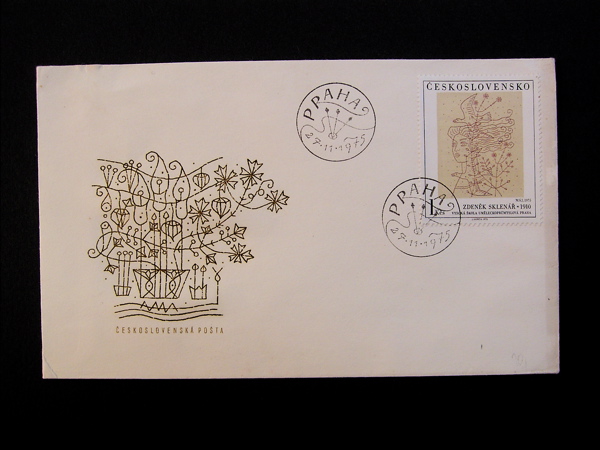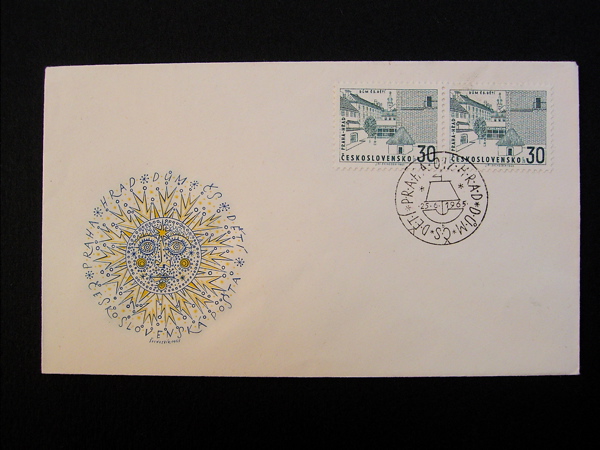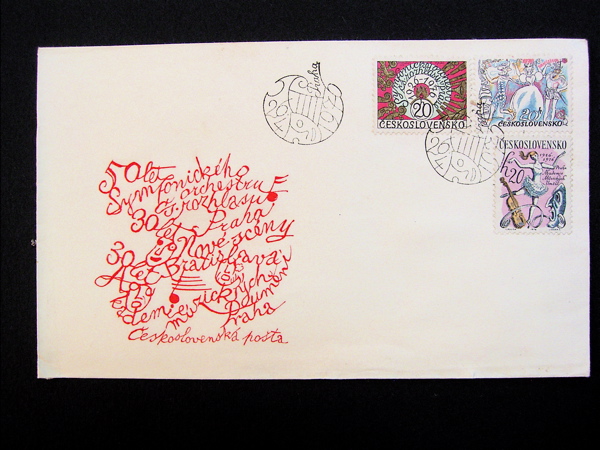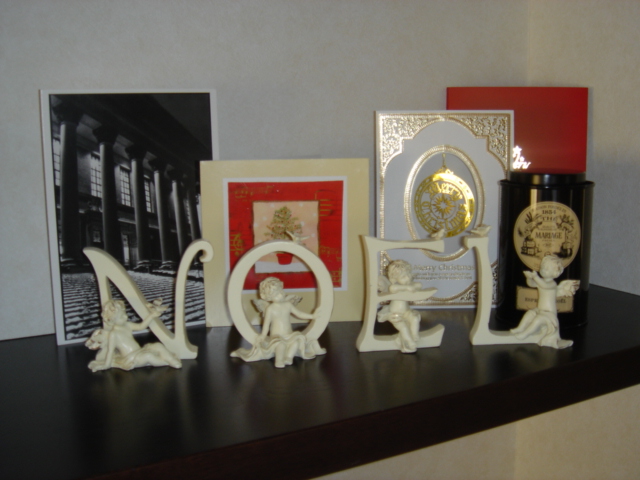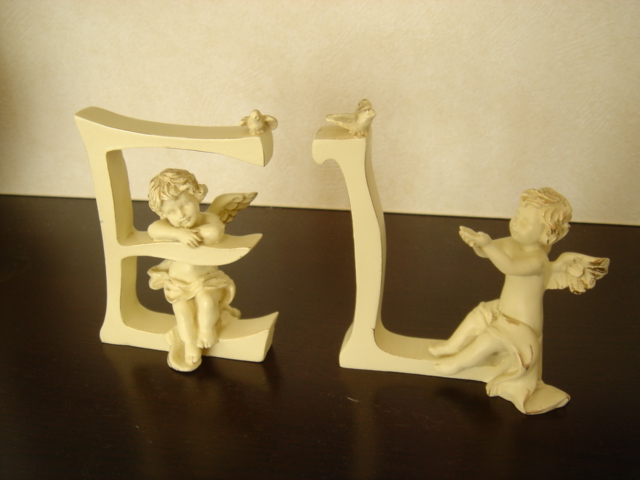
クレーのビュルギ・スケッチブック
大掃除をしていてもなかなか片付かないのは、整理する時にいちいちじっくり見入ってしまったりするからなんですよね。
きのうはパウルクレー協会会員限定版のビュルギ・スケッチブックのファクシミリでしばらく時間をとってしまいました。
寸法や体裁ともにオリジナルにかなりの程度忠実に模しているそうです。製本まで全部手作業の布張りのスケッチブックです。小さなサイズですが、中身は濃い!持っているだけで満足のスケッチブックなのです。
しかし、それも面白いのですが、一緒について来た解説本がもっとおもしろい!。私は初めて見ましたが、製本前の状態で送られてきているのです。
寒冷紗まではついていますが、表紙はなく、中身のページも袋状ですし、天地も小口も切る事を前提としてトンボが付いています。
これをどんな風に製本するかは、所有者のお好きな様に、と言う訳なのでしょう。
私の近くには、とてもユニークな製本をしてくれるモジトルのメンバーがいますので、イメージが固まったらお願いするつもり。それを考えるだけでも楽しみです。
手帳は何をお使いですか
早いもので明日は大晦日です。手帳もカレンダーも2005年版さようなら、ですね。コーヒーこぼしちゃってやけにふくらんでしまった
今年の手帳よ、ご苦労さん。
先日来年用の手帳を買おうとお店に行きましたが、ゆっくり選ぶ時間がなくて例年と同じものを購入してしまいました。
このところ使っているのはQuo Vadisのもので1週間見開き、時間が縦に刻んであるタイプです。
予定を書き込むには便利、でも無地のページがもっとあるといいな、とか日曜の欄が小さいので使いにくいな、などなどちょっとした不満はあるものの・・・文庫本サイズなのは気に入っています。
カバーは革製、ビニール、いろいろ選べます。ソニープラザには環境に配慮したカバーというのもありました。革のいいのを買おうか、他の手帳に乗り換えようか、それはまた来年考えることにして。
写真は、ちょっと飽きてしまったし寒いので冬バージョンに変身したカバーです。毛糸モコモコをくっつけて気分だけも暖かく。
アンネの日記
大掃除をしていたら古びた新聞が出てきました。以前気になって取っておいた1998年5月朝日新聞日曜版です。
「100人の20世紀」というシリーズで、この回はアンネ・フランクでした。
まず目に留まったのは、この壁に書かれた文字です。アンネが通っていたアムステルダムのモンテッソーリ・スクールが戦後アンネを記念して、アンネ・フラン ク・スクールと名付けられました。道路に面した壁には日記の一節が書かれています。壁と文字の色は紫とオレンジで、はっと目を引きます。 手書きの文字なので、訴えかける力が絶大です。
この壁に書かれた一説が日記のどの部分かはわかりませんが、私は何度か彼女の書いた文章をカリグラフィーの作品で使っています。特に有名なのはこの文章です。
In spite of everything, I still believe that people are truly good at heart.
「すべての状況にも関わらず、人々が心の中では本当は善良なのだと私は信じています」
(一節の全文は追記の方に書きましたので、そちらをご覧下さい)
たとえ大きな絶望の中でもけなげに希望を持っていた十代の少女の書いたこの文字を見ると、世の中に戦争がなくなり平和な世界が来るようにと、祈らずにはいられません。
来年が争いのない平和な一年になるといいですね。
この大掃除に出て来た黄ばんだ新聞。捨てずに取っておこうと思います。
粘土のアルファベット
以前、ブログで粘土のアルファベットを紹介しましたが、自分でも作ってみたくて、制作者の小松さんに粘土のアルファベットの1day ワークショップをしていただきました。
平らな粘土の上にアルファベットの切抜きをおいて、カッターを使って、形を切り出していくのですが、刃を垂直に入れて切り出すのがなかなか難しく、集中力のいる作業でした。切り出した後は、表面をならす作業がやりやすいのですが、なかなかフゥ...... ならしながら、先生のかわいいでしょ!という言葉が印象的。確かになでなですると可愛い気になってきます!要領を得た方々は、どんどん進んでできていましたが、私はといえば、1回で1個がようやくなもので、3回にわたってやって、ようやく3種を作りました。
写真奥のMO、モノグラムに挑んだ1作目、これは大変でした。途中で割れてきてしまいましたが、お助け、先生の技に感心!2作目ABC、2回にわたって作り、なんとかABCになりました。乾いて立たせたら、Bがひっくり返ったけれど,,,,,、3作目、noel、全WS終了後、夜ひとりやって仕上げました。ABCもnoelも形がコロンとしていてかわいいです!白い粘土のほうがよかったかなあ。
初めての粘土、とっても新鮮で楽しかったです!カリグラフィーでもいろいろな工夫された道具の数々見てきましたが、粘土用の先生の手作り道具にはホ〜!でした。手作りの醍醐味を感じました。
書くだけではなく、何か手で作るという楽しさは、心を豊かにしてくれます。1年の締めくくり、あったかな気持ちになったワークショップ。小松さんありがとうございます!!!
懺悔のシーズン
国内では三連休のクリスマス行事も終わり・・・お正月に向けて街が変化しつつあります。
日本独特の風景ですね。
キリスト様の国では1月の三聖節(6日かな?)まではクリスマスっぽい雰囲気が続くようですから・・・。
さてさて・・・今年も「やってしまった・・・懺悔のシーズン」です。色味のない部屋を楽しくしてくれたgreeting cardたち。みんなからの優しい心遣いが伝わってきて、冬の季節なんか吹き飛ばしてしまいそうな暖かさで身体も心も包まれます・・・。
それなのに・・・、私といえば、サンタとの交流は断ち切り、25日に海外向けのカードを必死に書き上げていたのでした。もう聖なる日になんか間に合いません!日本人的に「new year!」を勝手に押し付けているのです〜。
時々は間に合ったりもしますが、大抵はズレにズレコミます。そんな私のカードでも海の向こうのみんなは喜んでくれるわけです!「あ〜、神様よりきっと優しい!」
e-mailの手軽さもありますが、やはり手書きが・・・形あるものが・・・絆を深めます。毎年そんな風に感じます。
ちなみに・・・サンタはカトリックの国では活躍しないそうですね・・・。ドイツ語の先生が説明してくれました。オーストリアから来ていた先生でしたが、「サンタなんかいないよ!クリストキントだよ!」って言ってました。クリストキント=幼キリストですね。
まぁ、世界の半分以上はクリスマスは祝わないわけですから・・・などと言い訳、言い訳!心から懺悔して・・・来年こそは・・・鬼も笑っちゃうような決意です!
チェコの封筒デザイン
クラスの生徒さんのE子さんが,教室に持って来て見せて下さったチェコの封筒デザインです。ほとんどが1960年代のアンティークもので、切手と消印と封筒に印刷されている絵が一体になった実にと〜っても不思議な一品なのです。
クリックして拡大版をじっくり見てください。切手のデザインが消印にも生かされていて、さらに封筒に印刷されている絵にも同じデザインが繰り返されていま す。先に切手と消印があって、それに合わせて印刷したのでしょうか。面白い線で書かれている文字が何とも言えず、いい味を出していますよね。
このアンティークの封筒は大阪の有名な雑貨屋さんでみつけたそうです。こんなお宝、私もみつけてみた〜い!!
天使といっしょに
文字好きを公言しているので、それに関わるものをいただくことは多いのですが
今年のクリスマスには文字そのものというプレゼントをいただきました。
このNOEL、一人ずつ天使が共にいるのです。
腕にあごをのせている天使もかわいいですね。何か考えごと?Lの文字がちょっと手前にかしいでいるのも手作りふうで味があります。
色はアイボリーと少しの金色。カードを置いている棚に早速飾ってみました。いつもの棚が優美な空間に!